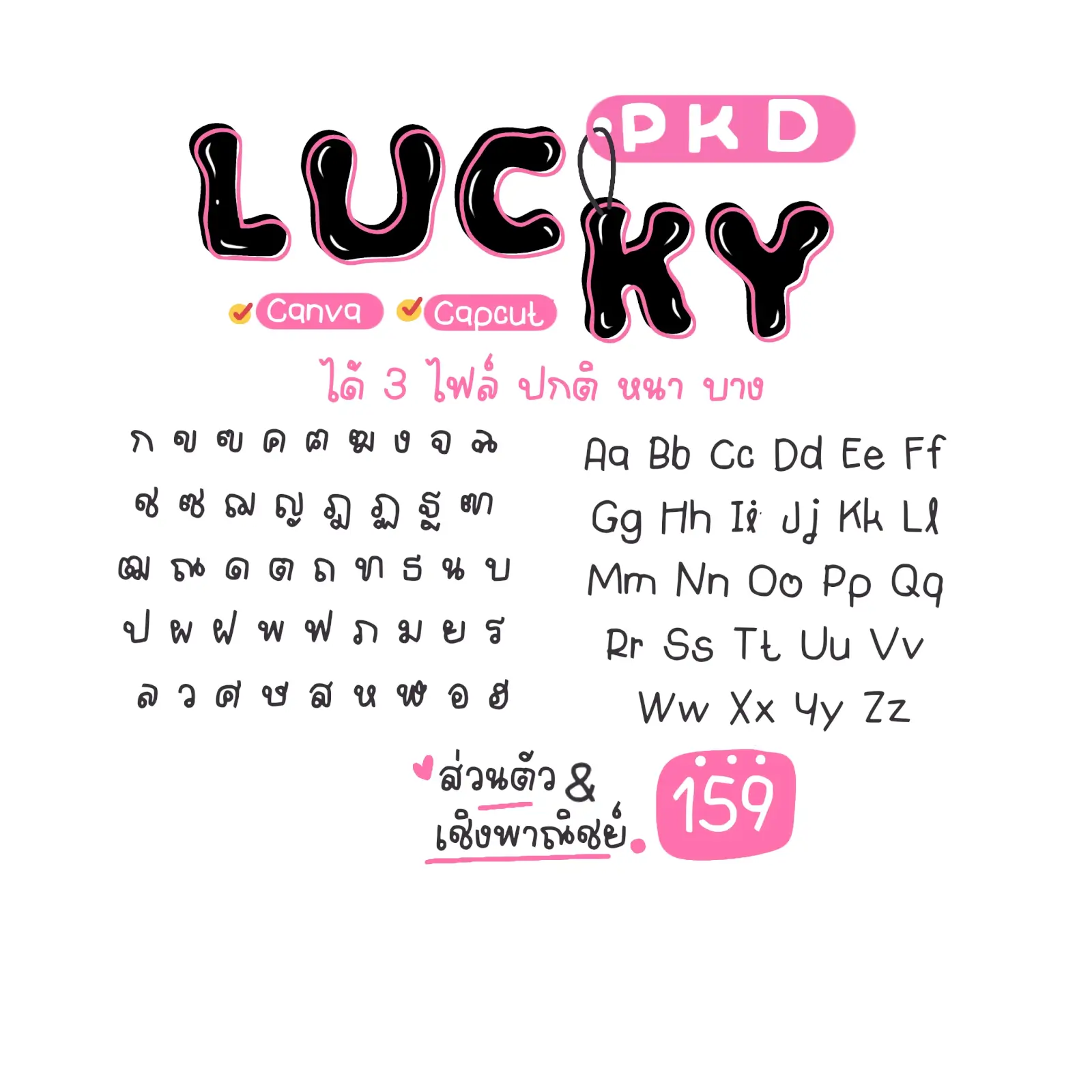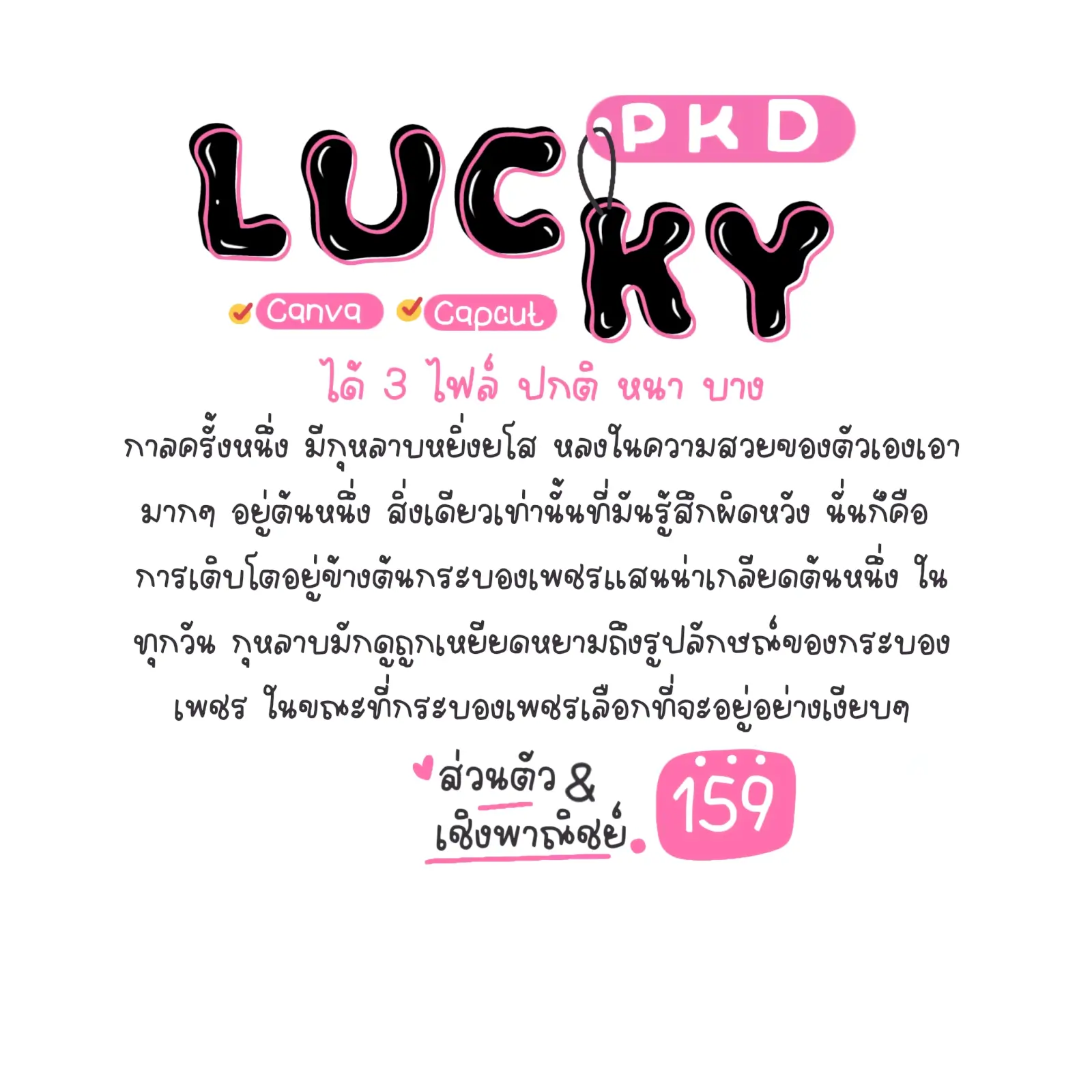
ลัคกี้ฟอนต์ (PKD Lucky) – ฟอนต์ลายมือน่ารัก สดใส เป็นกันเอง เหมาะสำหรับงานคอนเทนต์ โพสต์โซเชียล สติกเกอร์ คาเฟ่ และงานออกแบบทั่วไป
- รองรับภาษาไทย ภาษาอังกฤษ ตัวเลข และสัญลักษณ์
ลัคกี้ (PKD Lucky)